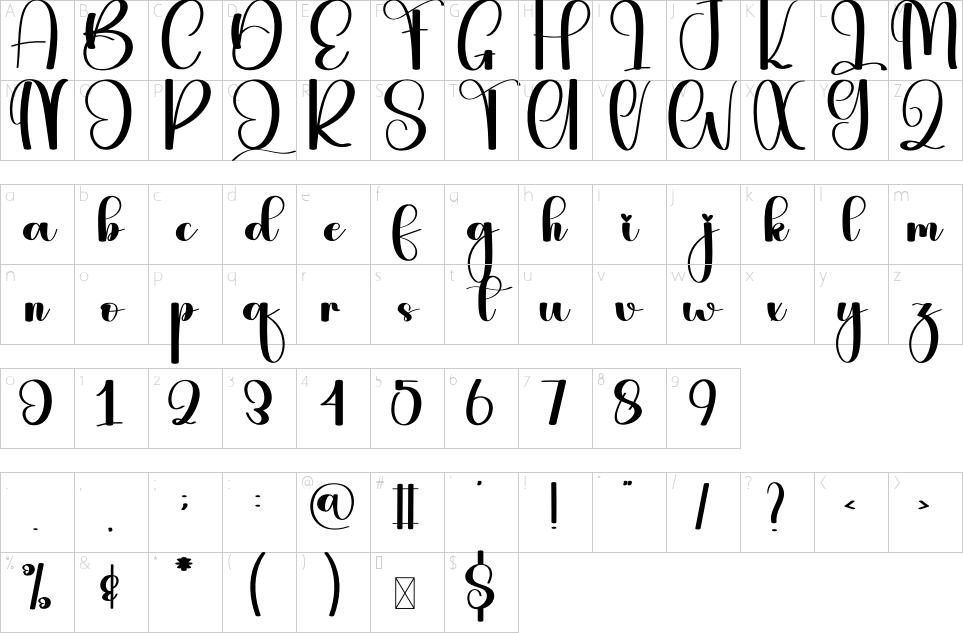
A Mountain Font é uma elegante escolha para seus projetos digitais, especialmente se você procura uma fonte com um toque natural e descontraído. Essa fonte foi criada pelo designer desconhecido e já foi baixada 544 vezes. Suas linhas suaves e formas curvilíneas criam um efeito harmonioso que se sobressai em qualquer layout. Ideal para textos como subtítulos, cabeçalhos e até mesmo para gráficos em posts de blog, a Mountain Font adiciona um toque único e natural a qualquer projeto. Engane-se e experimente a Mountain Font para adicionar um pouco de frescor e originalidade ao seu design.